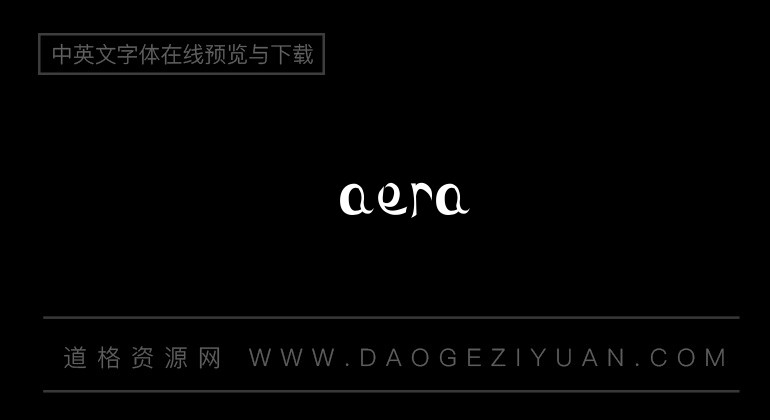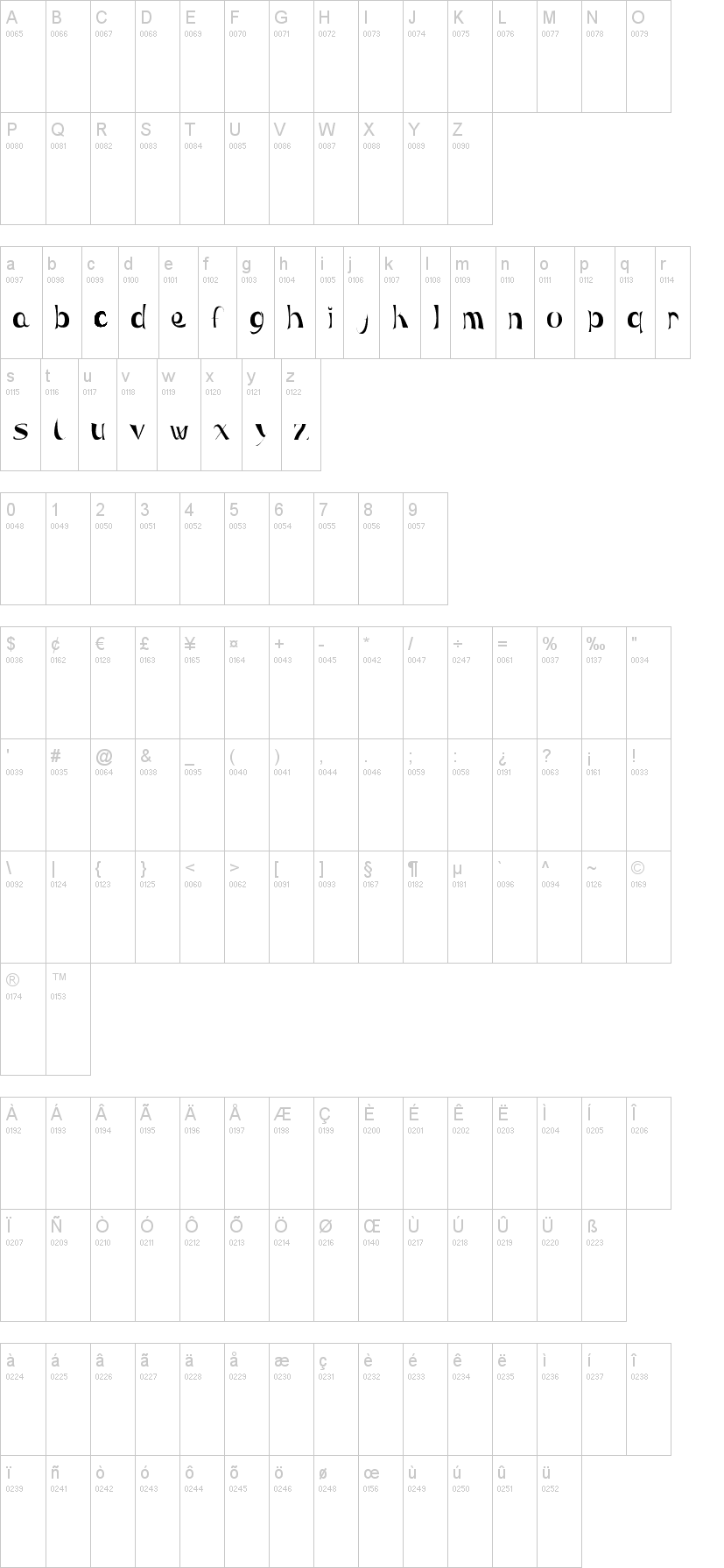
Maera 字体是一款由西班牙设计师 Josep Patau 创作的一款新型字体,它具有独特的外观和设计,可以满足不同的设计要求。Maera 字体具有明亮、清晰的外观,它的字体设计有着柔和的曲线和精细的细节,使用 Maera 字体可以让文字更加突出,更具有吸引力。Maera 字体还可以用于网页、报纸、书籍等各种印刷品的设计,以及电脑程序的界面设计,给用户带来良好的视觉体验。内容介绍
Maera是一款非常不错的手写艺术字体,具有很好的视觉感,适合于文化类的宣传设计、商业类品牌的广告和产品包装设计以及个性化文字排版等较多场景。